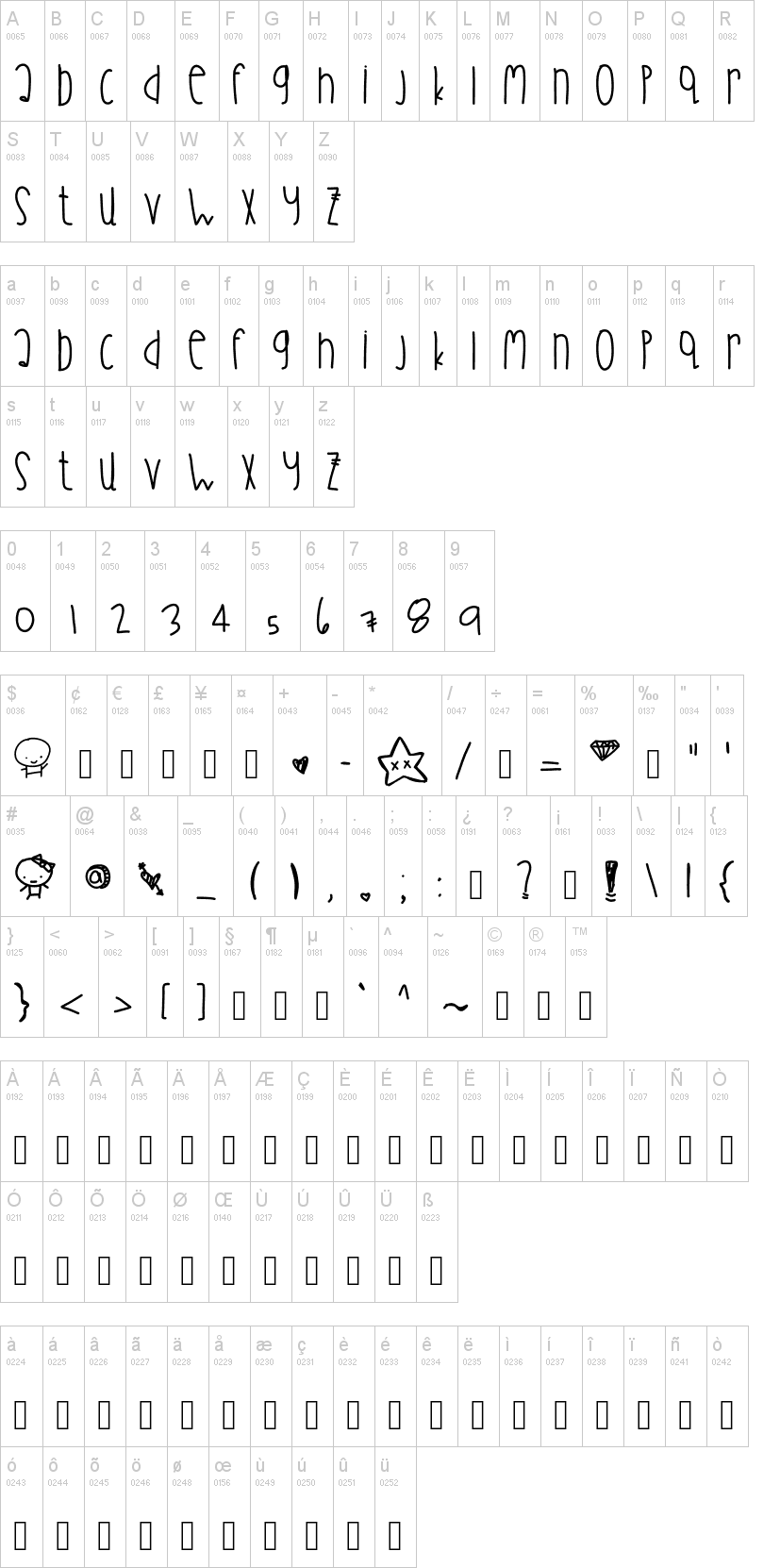
Day Dreaming
Day Dreaming是一款字体,它的特点是清新、轻盈和富有趣味性。它的字形有些许不规则,但整体上仍然保持了字体的可读性。Day Dreaming字体的笔画流畅,具有良好的可读性,因此非常适合在海报、卡片、包装设计和其他创意设计项目中使用。它的设计灵感来自于手写字体,能够让你的设计作品看起来更加自然、舒适和吸引人。Day Dreaming字体还有一个值得一提的特点是它的斜体字非常漂亮,可以让你的设计作品更加生动和迷人。
Day Dreaming是一款非常不错的手写艺术字体,具有很好的视觉感,适合于文化类的宣传设计、商业类品牌的广告和产品包装设计以及个性化文字排版等较多场景。